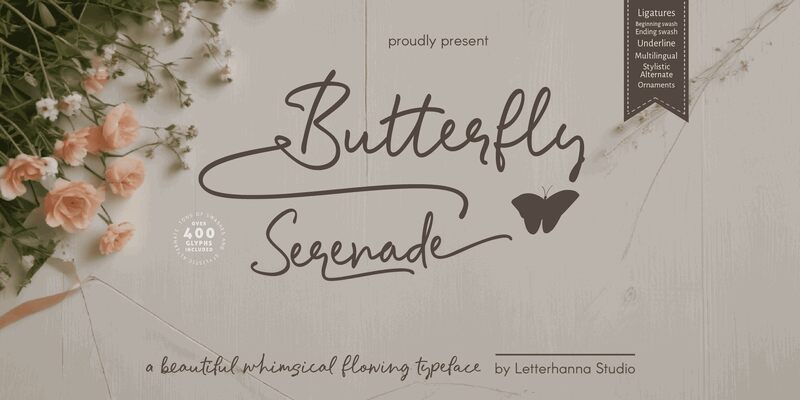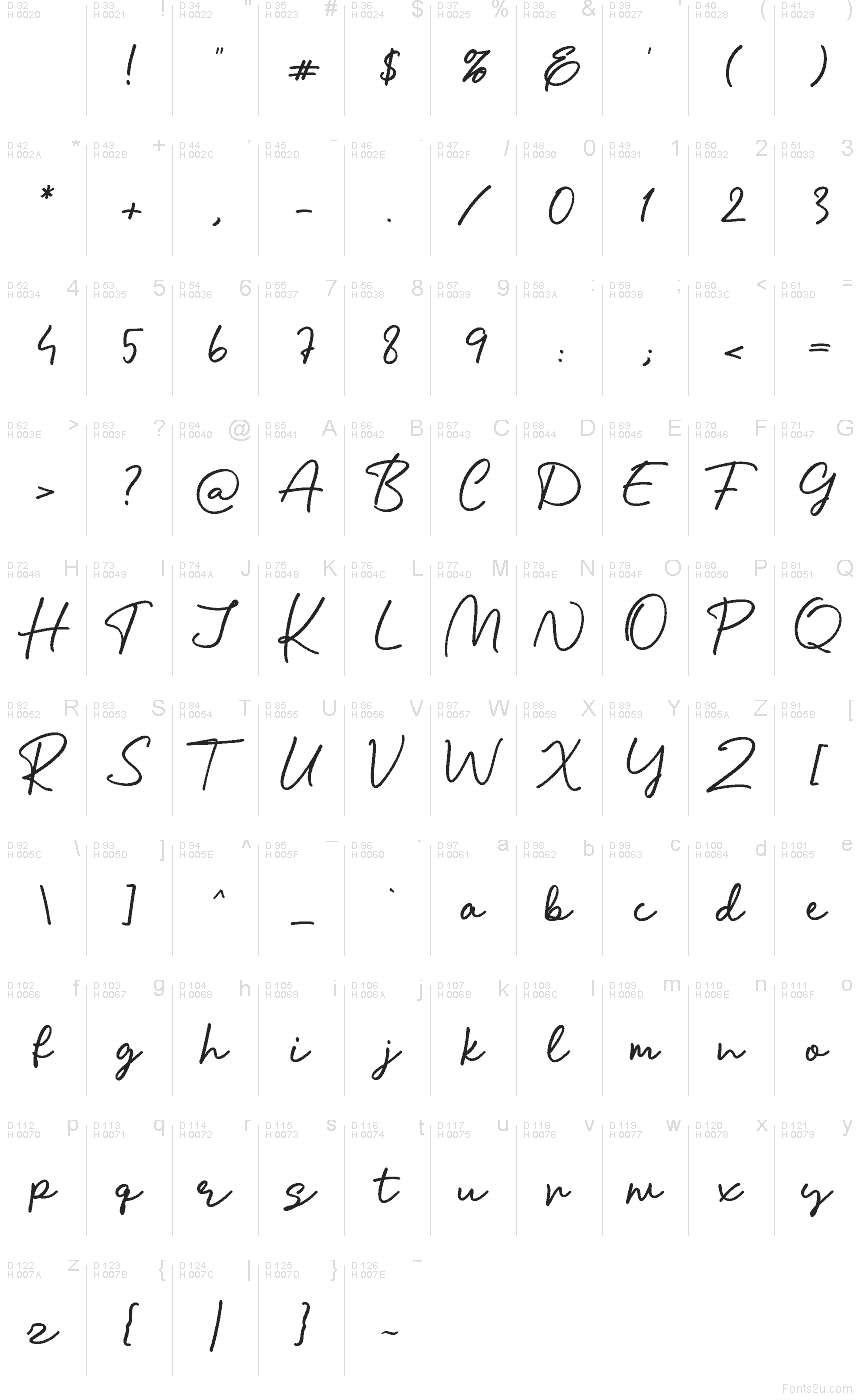
Butterfly Serenade, creata da Rinaldo Hasibuan di Letterhanna Studio, è un font scritto a mano che richiama la naturalezza dell'inchiostro su carta. I suoi tratti lunghi e sinuosi e il ritmo rilassato ricordano una firma spontanea: fluida, ariosa e dal tocco romantico, pur rimanendo sempre perfettamente leggibile a colpo d'occhio.
Butterfly Serenade è perfetta per inviti di nozze, branding nel settore beauty, loghi di boutique, citazioni per Instagram, etichette, menù di caffè e biglietti di auguri. Usala in dimensioni generose per far respirare le sue curve e abbinala a un font sans serif discreto, come Montserrat o Lato, per i dettagli: questo font gratuito darà un tocco speciale ai tuoi titoli.
Butterfly Serenade
Introducing Butterfly Serenade, a whimsical handwriting script font that dances across the page with effortless charm. Inspired by the graceful flutter of butterfly wings, this font combines delicate loops and playful flourishes to create a light, airy feel thats perfect for adding an enchanting touch to invitations, greeting cards, or whimsical branding. Each letter is crafted to bring a sense of warmth and creativity, making your designs as delightful and unique as a garden in bloom. Let Butterfly Serenade take your projects to new heights of elegance and imagination!